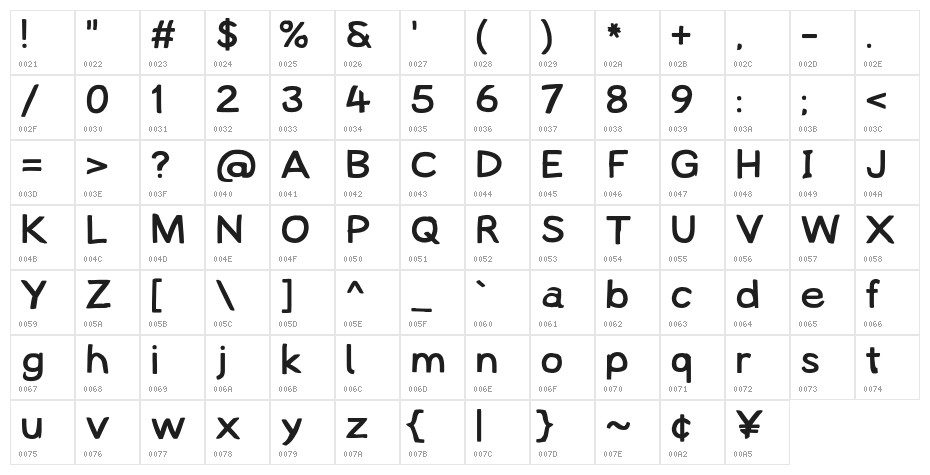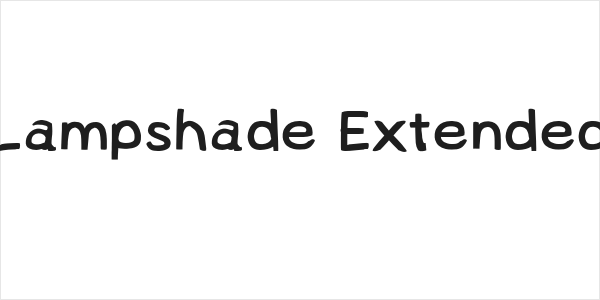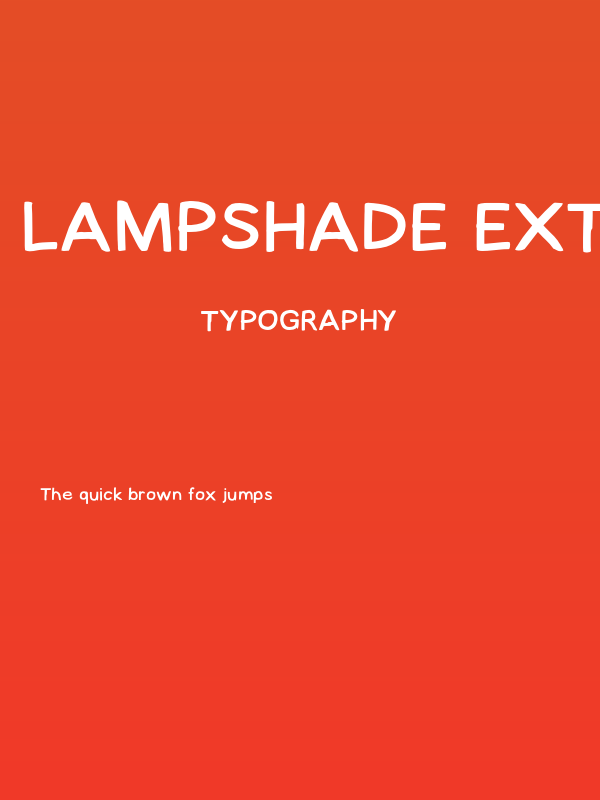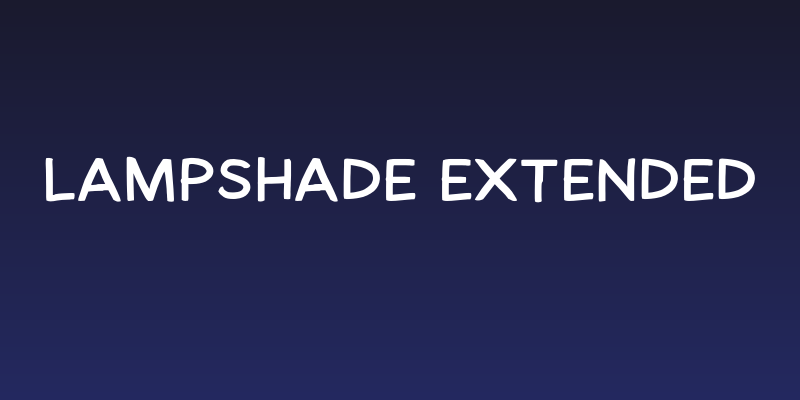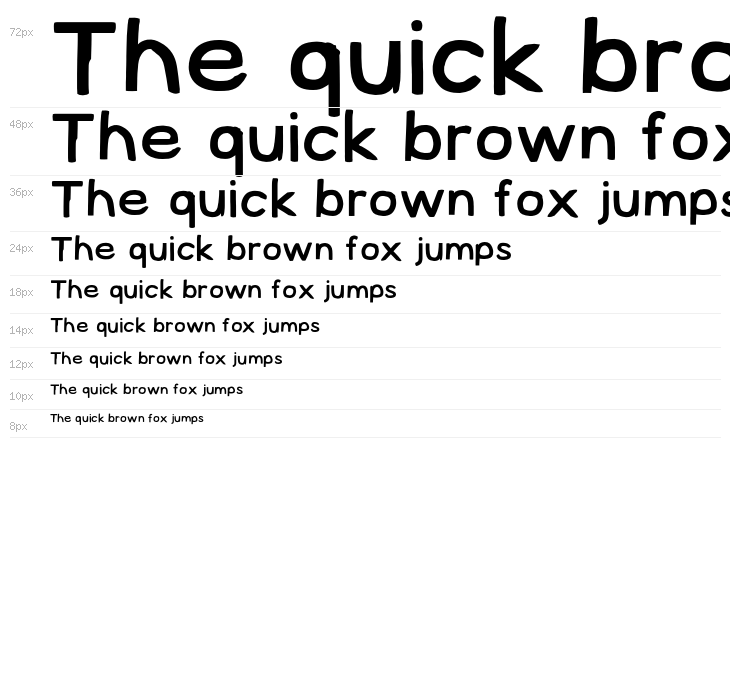
Lampshade Extended Font
| Larghezza | Expanded |
| Caso d'uso | Headlines, Logos, Casual Text |
| Progetti proposti | Ideal for children's books, playful branding, casual invitations, and friendly advertisements. |